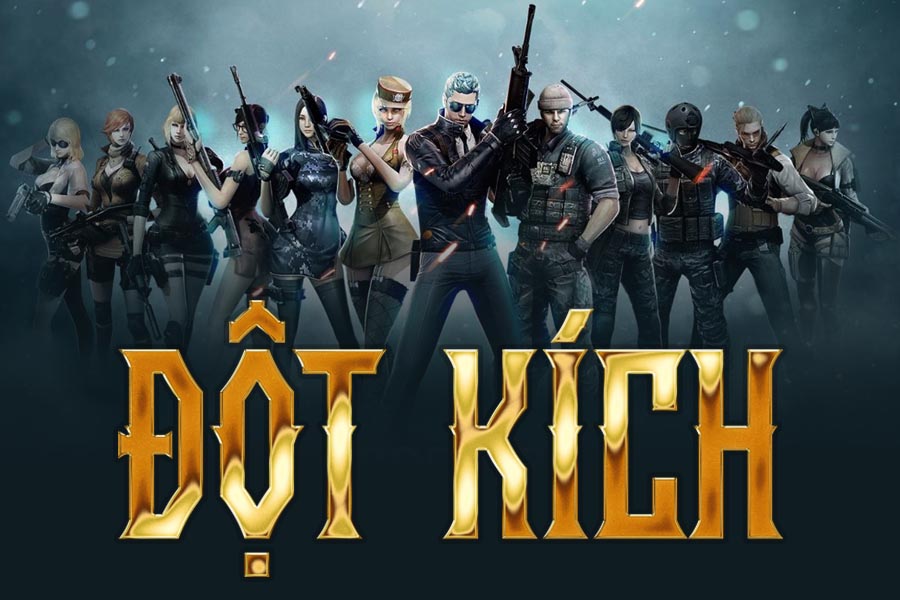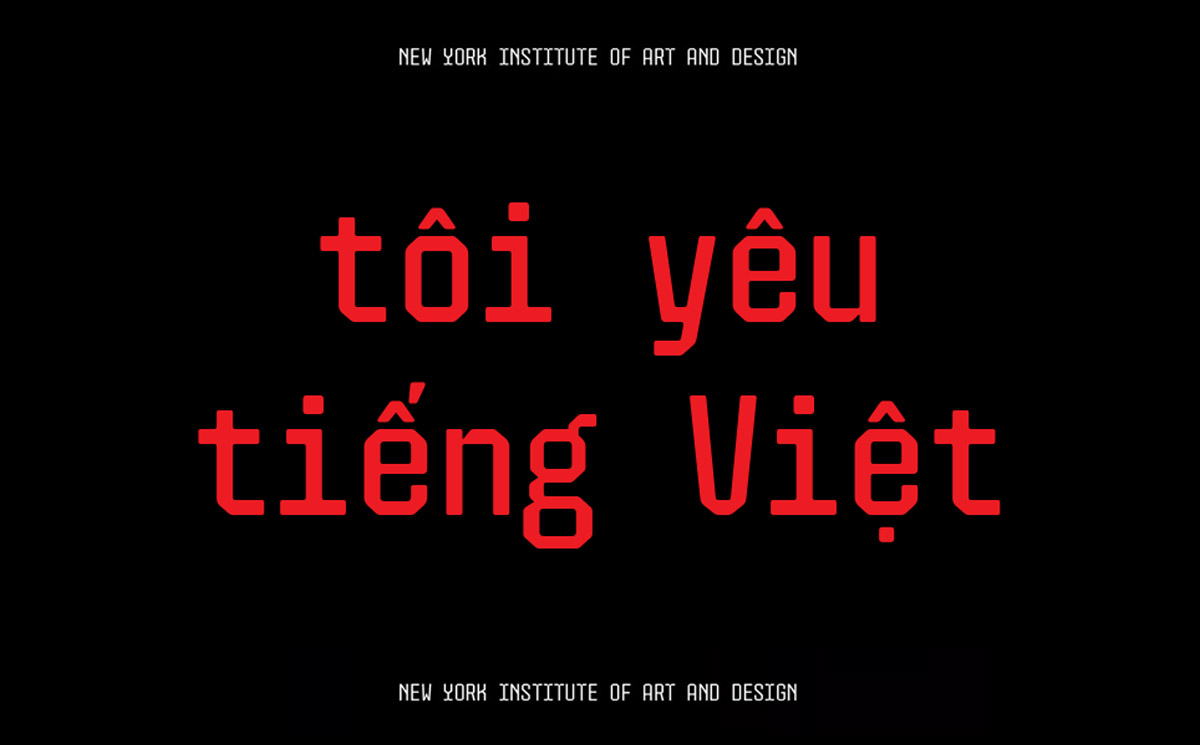
[Tải Xuống] TOP 10 Font Chữ Quân Đội Mạnh Mẽ Việt Hóa Đẹp Nhất 2025
1. Font chữ quân đội là gì? Lịch sử và nguồn gốc
Font chữ quân đội (military fonts) là nhóm font được thiết kế với cảm hứng từ chữ stencil in trên quân phục, khí tài, bảng hiệu trong quân đội. Đặc trưng bởi nét chữ cứng cáp, sắc nét, hình học, chúng thường mang đến cảm giác mạnh mẽ, dứt khoát và chuyên nghiệp.
Khởi đầu từ nhu cầu in nhanh và rõ ràng trong môi trường quân sự, các font stencil dần được biến tấu thành nhiều phong cách hiện đại, phù hợp cho thiết kế banner, poster phim hành động, áo thun lính, giao diện game chiến tranh.
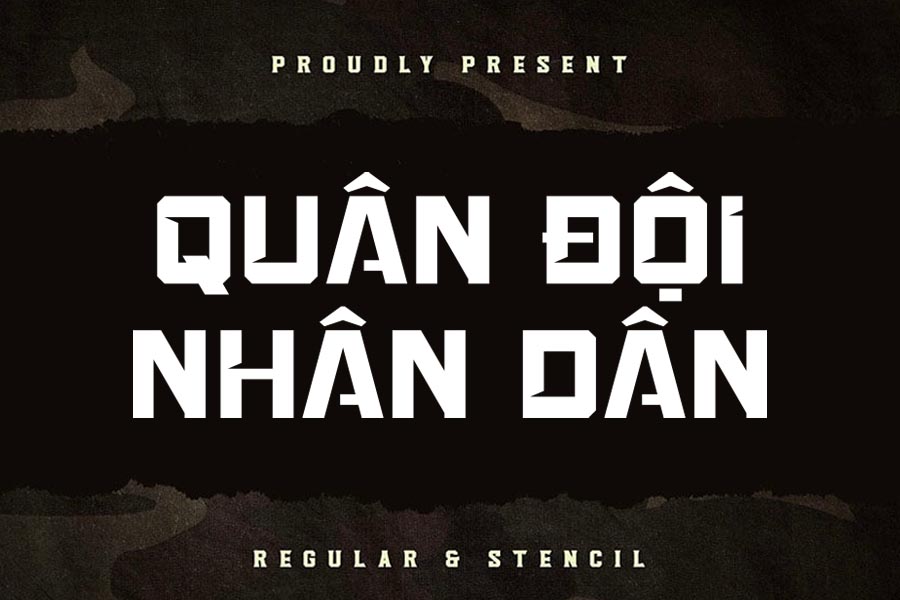
2. Đặc điểm nhận diện của font chữ quân đội
- Nét cắt stencil – các phần chữ thường bị "rời nét" như ký hiệu quân sự
- Kiểu dáng hình học, khối chữ mạnh – truyền tải sức mạnh và sự kỷ luật
- Tông màu gợi ý khi dùng: xanh lính, đen, be, cam cháy
- Dễ phân biệt với font retro, vì thường mang tính biểu tượng hơn là trang trí
3. Danh Sách Top 10 font chữ quân đội Việt hóa 2025
1. TH Army Rangers – Phong cách stencil đậm chất quân đội cổ điển
TH Army Rangers tái hiện rõ tinh thần quân sự Việt Nam qua từng đường nét stencil mạnh mẽ, như những dòng chữ in trên thùng đạn, băng rôn cổ động hay biển báo chiến trường. Nét chữ vuông vức, rắn rỏi gợi nhớ đến khí chất của người lính – kiên cường và dứt khoát.
Điểm nhấn độc đáo là ngôi sao năm cánh được chèn khéo léo vào các chữ cái thường, mang đậm dấu ấn quân đội nhân dân Việt Nam. Font phù hợp cho thiết kế poster phim chiến tranh, banner tuyên truyền, hoặc giao diện game mô phỏng.
Thiết kế bởi Daniel Zadorozny, Việt hóa bởi Phạm Sơn, hỗ trợ đầy đủ tiếng Việt.
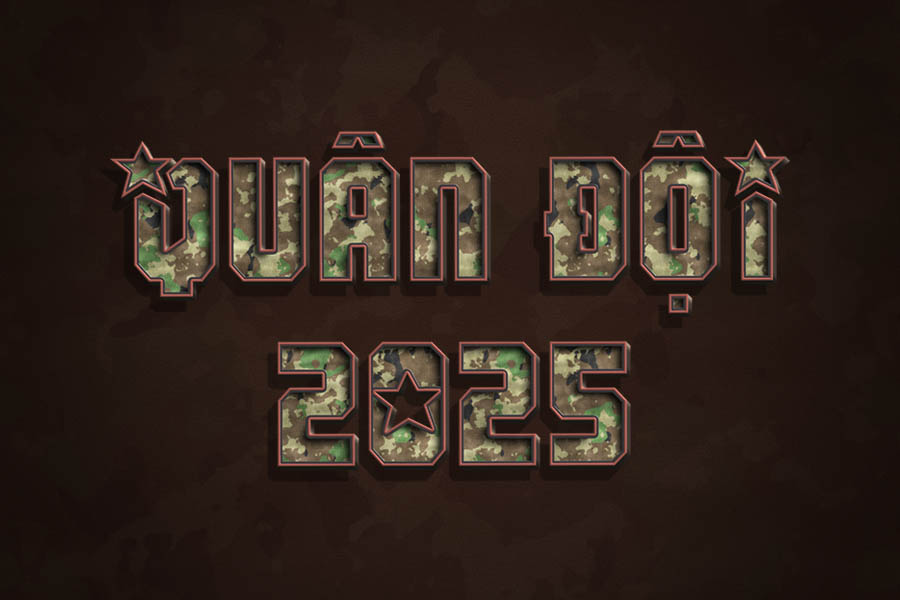
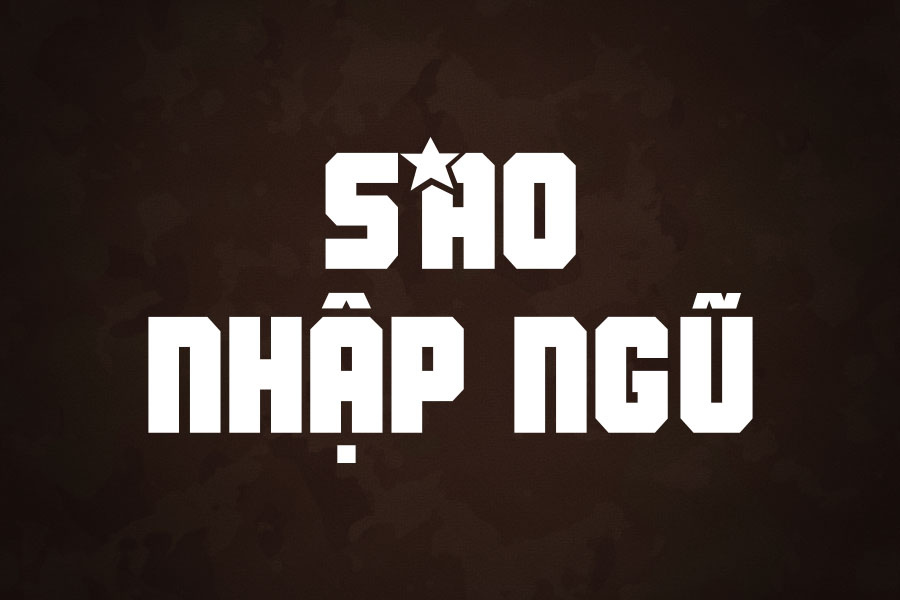
2. TH Hagsub – Font chữ thể thao, mạnh mẽ cho quân đội
TH Hagsub không phải là một font stencil truyền thống, nhưng lại mang trong mình sức hút đặc biệt nhờ sự cân đối, rắn rỏi và tính thể thao rất rõ. Với những đường nét cứng cáp, đậm vừa phải và phần chữ được cân chỉnh gọn gàng, font này rất hợp để làm áo đồng phục huấn luyện quân đội, banner các giải đấu chiến thuật hoặc branding phòng gym quân sự. Nhìn qua là thấy cảm giác tốc độ, sức mạnh, kỷ luật, tất cả trong một thiết kế.
3. Font chữ TH Aquxe – Phong cách sans-serif hiện đại, kỹ thuật
Nếu bạn đang cần một font vừa mang phong cách quân đội, vừa có vẻ hiện đại, phù hợp cho các giao diện công nghệ thì TH Aquxe là một gợi ý tuyệt vời. Với phần chữ sans-serif gãy gọn, khoảng cách hợp lý và độ đậm vừa phải, font này dễ dàng ứng dụng trong infographic an ninh quốc phòng, slide thuyết trình, hay tiêu đề trong các dashboard điều hành. Nó không mang màu sắc retro như những font stencil, nhưng lại đại diện cho hình ảnh quân đội hiện đại, công nghệ cao.
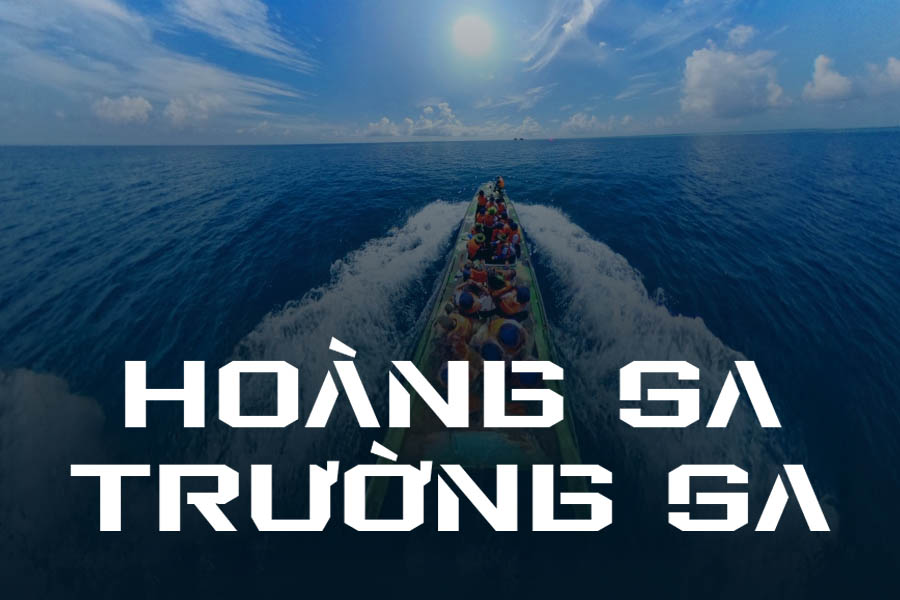
4. TH Blayzer – Font slab serif uy lực, đậm đà khí chất chỉ huy
TH Blayzer là lựa chọn số 1 cho các thiết kế cổ động, tuyên truyền hoặc poster có chiều sâu lịch sử. Font có phần chân đậm, mang hơi hướng slab serif mạnh mẽ, cho cảm giác của sự vững vàng, quyết đoán và quyền lực. Đặc biệt, với nét chữ dày nhưng không rối, TH Blayzer cực kỳ lý tưởng để làm banner ngoài trời, tiêu đề sự kiện quân sự hoặc các sản phẩm thiết kế cần nhấn mạnh yếu tố "tuyên ngôn".
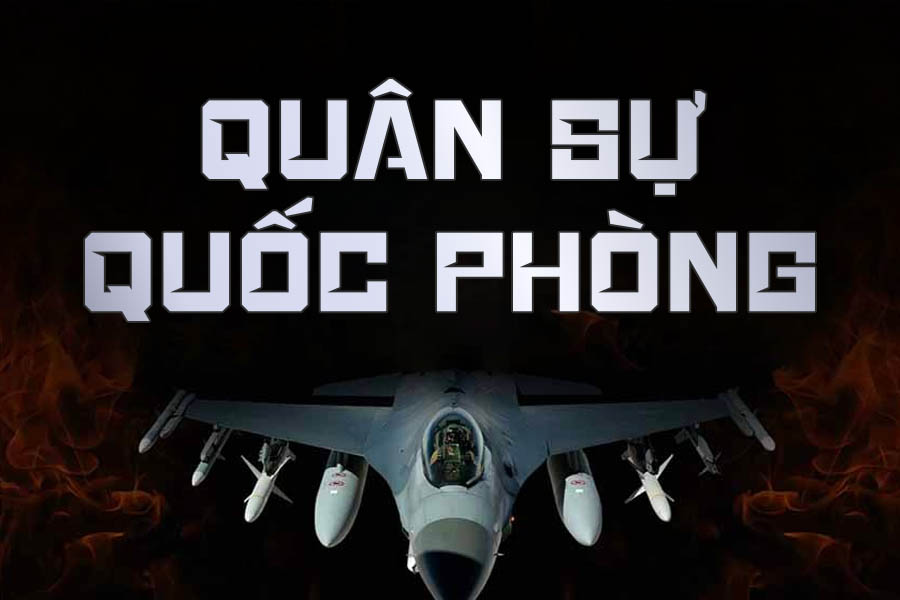
5. TH Striger – Font thể thao pha lẫn phong cách quân sự hiện đại
TH Striger có thể xem là “giao điểm” giữa một bộ font chữ thể thao và một bản thiết kế quân sự hiện đại. Các chữ cái cao ráo, nét dày vừa phải, đường gãy mạnh mẽ – tất cả đều tạo nên cảm giác chuyên nghiệp, năng động, phù hợp cho quân đội huấn luyện thể chất hoặc branding thể thao có yếu tố chiến đấu. Font này khá linh hoạt: vừa đủ mạnh cho quân sự, vừa không quá nặng để dùng trong các thiết kế trẻ trung.
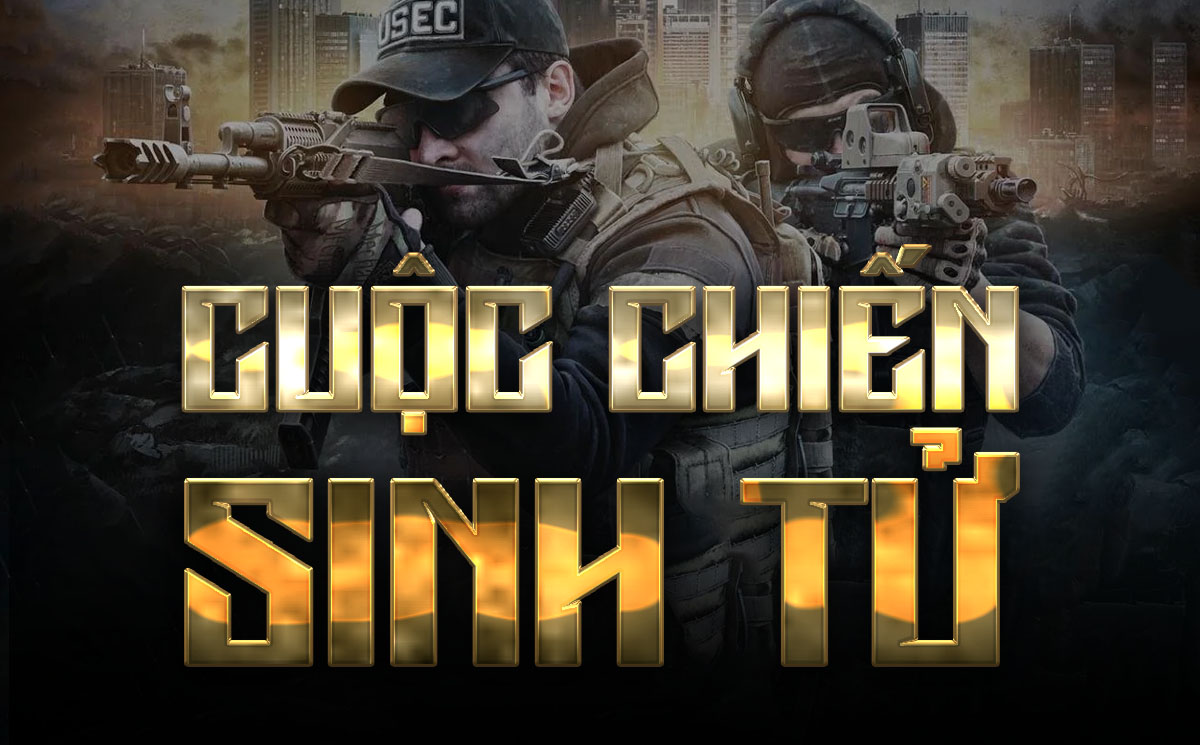
6. Font TH Cungcap 9 – Tinh thần chiến đấu thể hiện rõ qua từng nét chữ
TH Cungcap 9 được thiết kế mang đậm tinh thần của những năm tháng chiến đấu – với chữ stencil được cách điệu nghệ thuật nhưng vẫn giữ được sự cứng rắn, phóng khoáng và khô khốc. Font rất thích hợp để tái hiện bối cảnh chiến tranh, poster về lịch sử, banner cổ động cho ngày truyền thống quân đội hoặc các trò chơi có đề tài quân sự cổ điển.
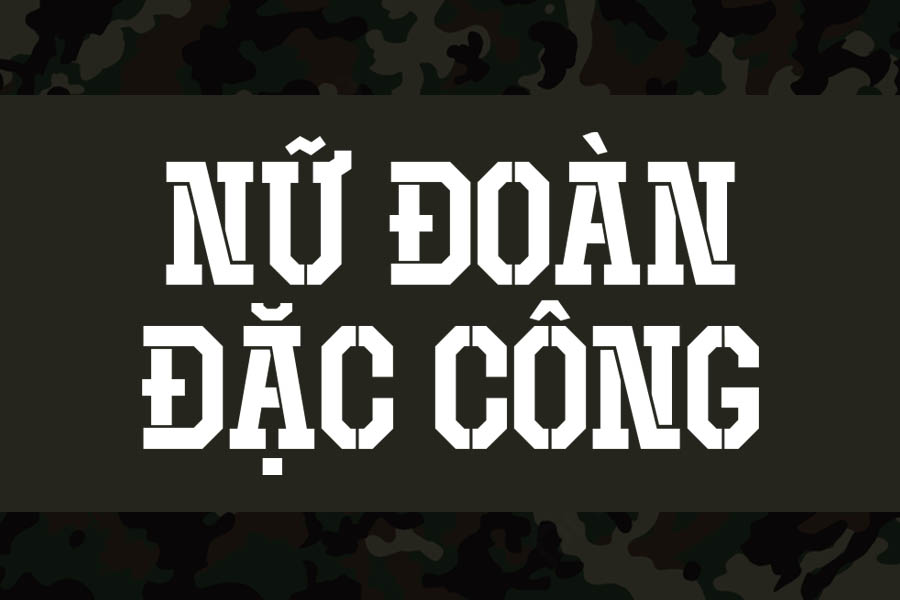
7. TH Westorn – Retro cổ điển pha chất cao bồi quân đội
Font TH Westorn là một món quà tuyệt vời cho những ai thích sự hoài cổ. Font mang đậm chất retro cao bồi miền Tây, nhưng khi kết hợp với chủ đề quân đội lại tạo nên sự mới mẻ không ngờ: vừa lãng mạn, vừa mạnh mẽ, vừa có chiều sâu lịch sử. Sử dụng font này trong các thiết kế phim ảnh, poster cổ động hoặc branding mang phong cách "cũ mà chất" sẽ cực kỳ nổi bật.
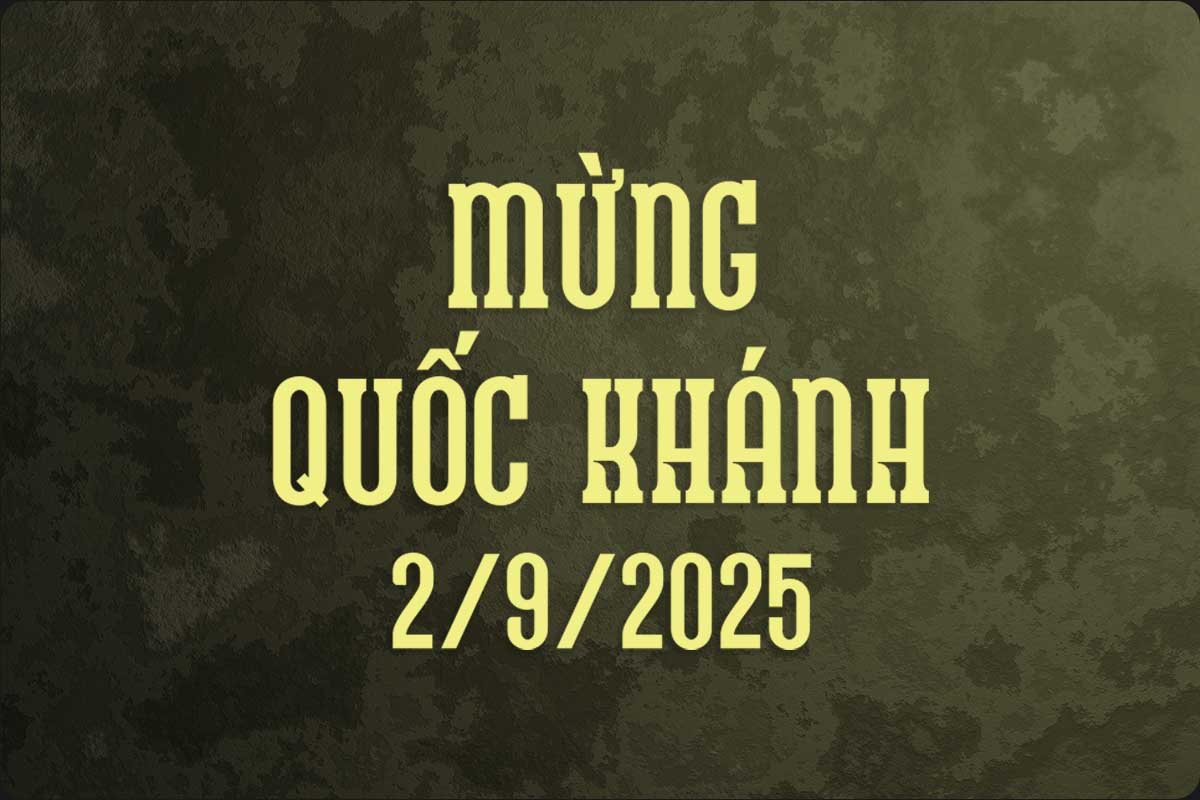
8. Morucas – Font display nghệ thuật nhưng không thiếu uy lực
Morucas là một trong số ít font display có thể kết hợp được yếu tố thẩm mỹ nghệ thuật và sức mạnh thị giác của quân đội. Với các chi tiết cách điệu độc đáo nhưng vẫn giữ tỷ lệ chuẩn, font mang lại cảm giác “nghệ sĩ cứng rắn” – rất thích hợp cho bao bì, tiêu đề phim hành động, hoặc logo mang cảm hứng chiến binh. Khi sử dụng Morucas, bạn sẽ thấy tính biểu cảm rõ rệt mà hiếm font quân đội nào có.
5. Tổng kết